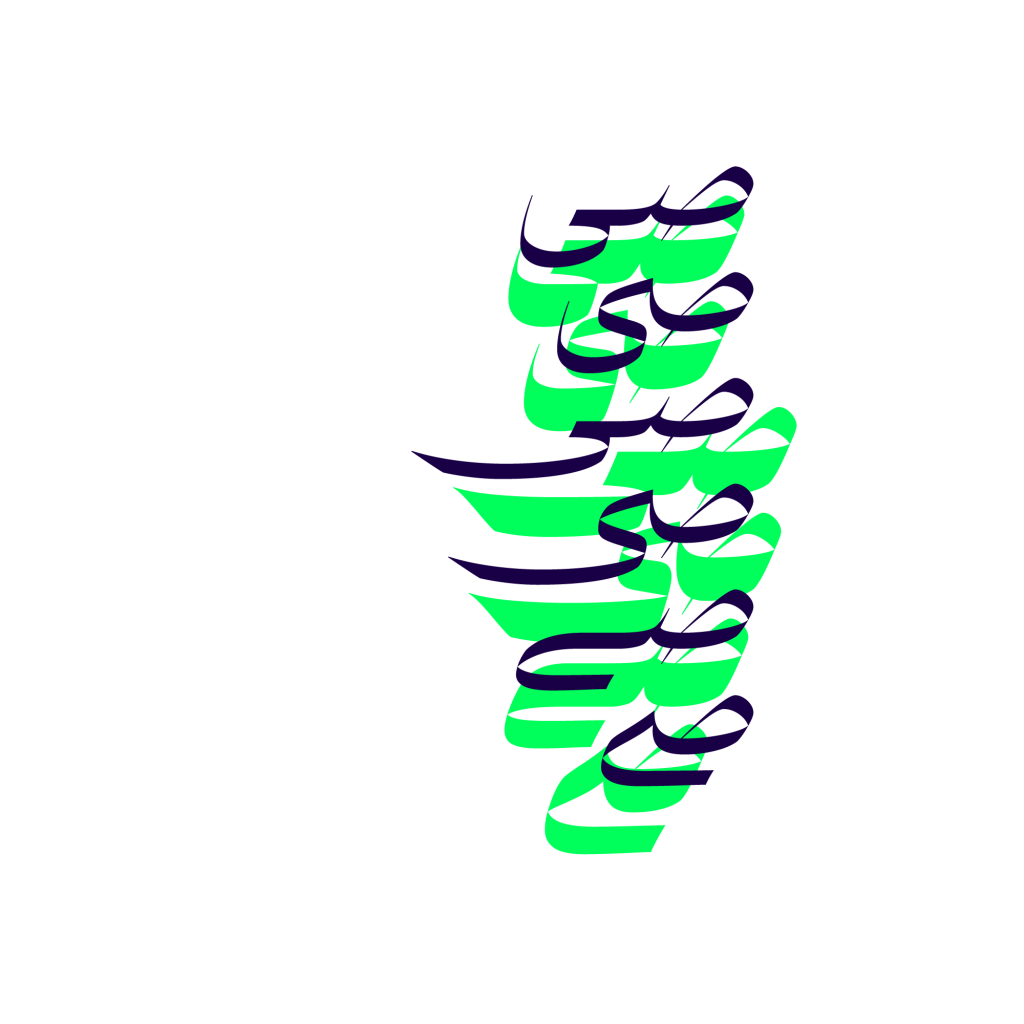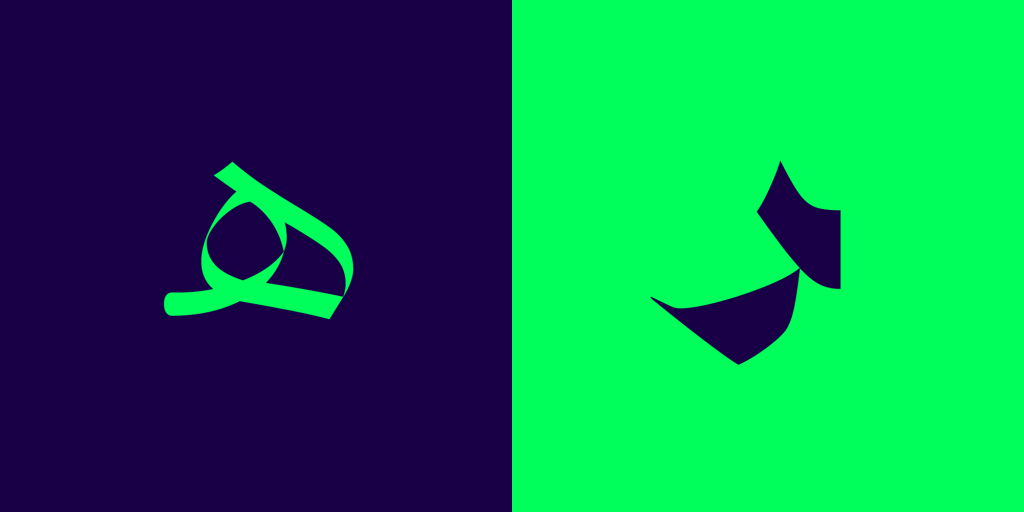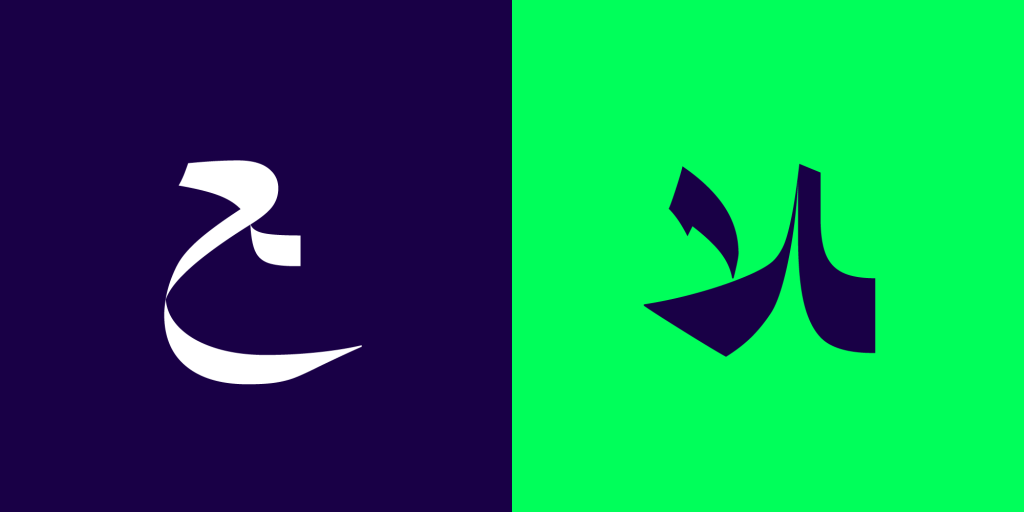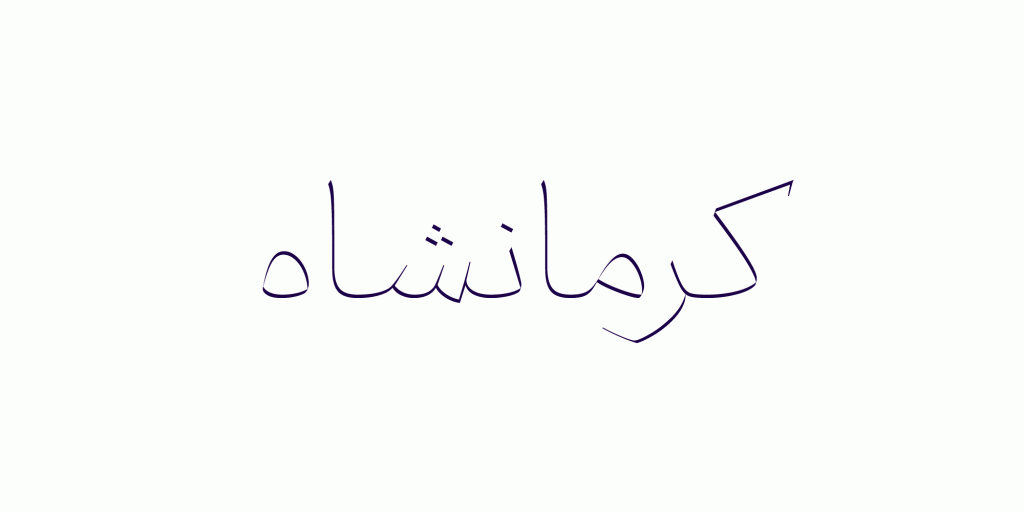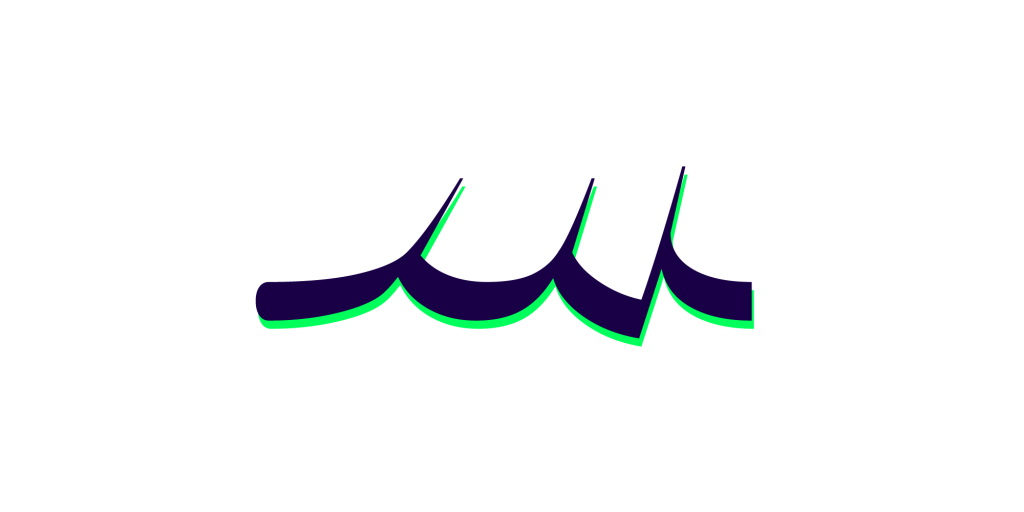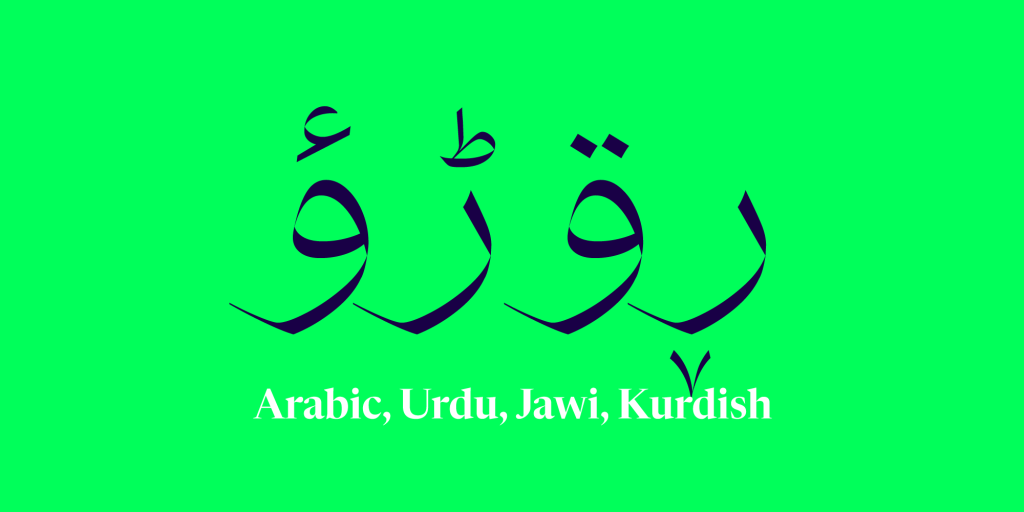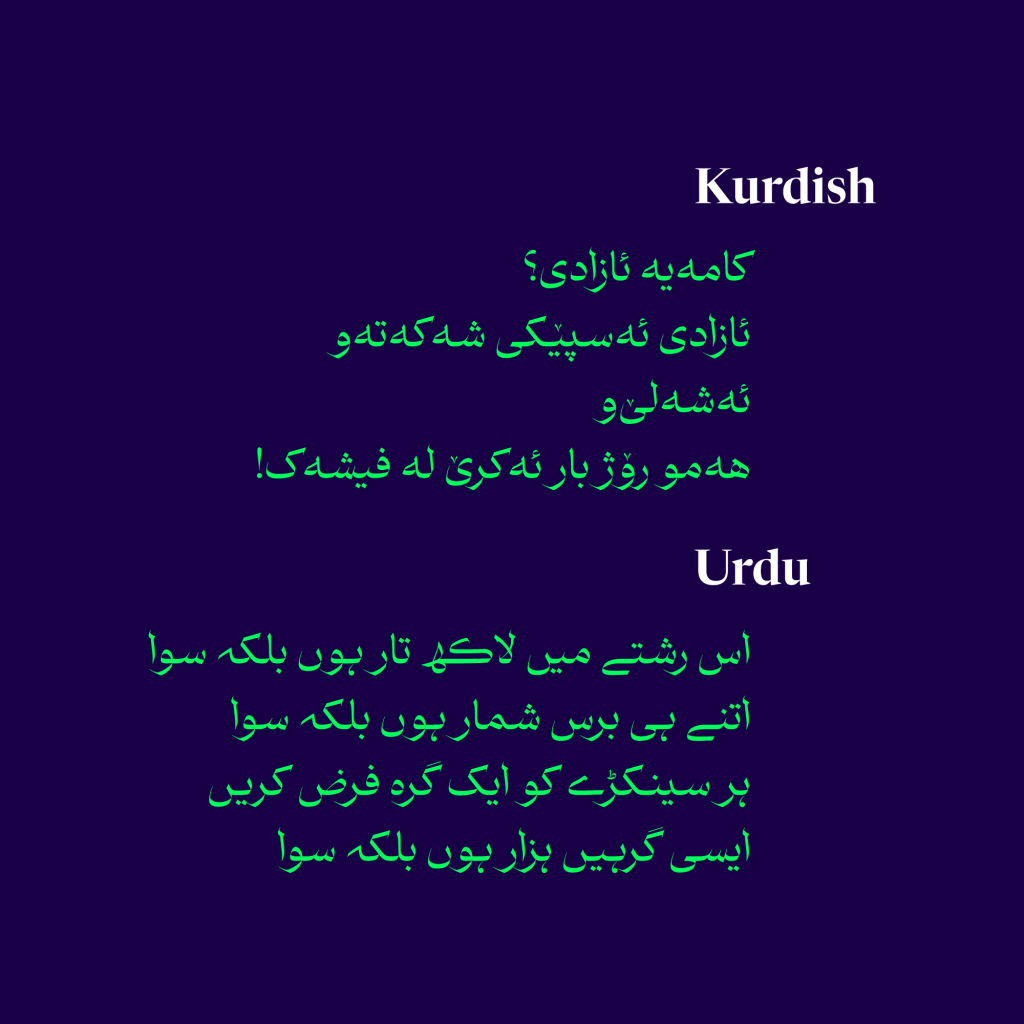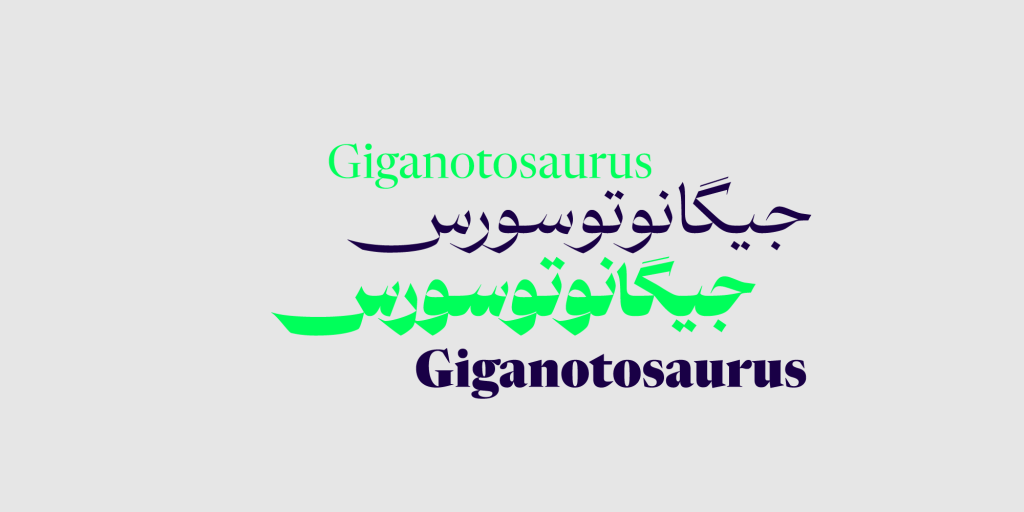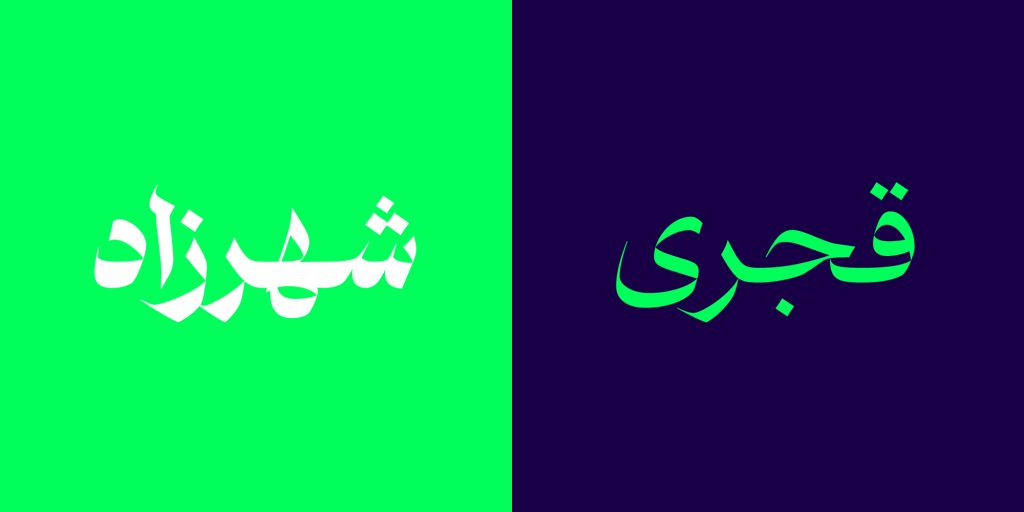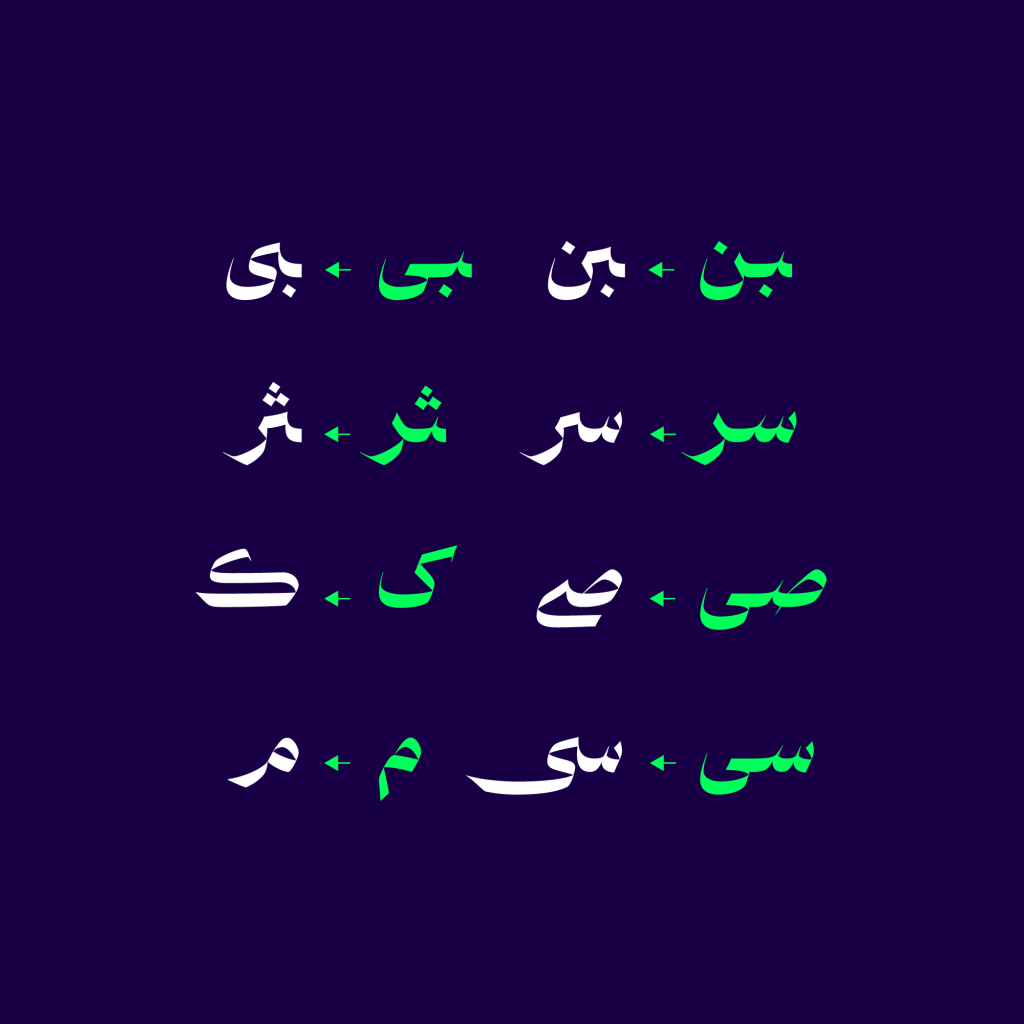
فونت پیکان قلمی که همانند نام پیکان تند و تیز و برنده است شجاع جسور و جدی است. این قلم از خانواده نسخ مناسب برای تیتر ها و متون کوتاه است تا نگاه مخاطب را در کسری از ثانیه جذب کند.
فونت پیکان قلمی با کنتراست ضخامتی بالا
قائده مند این خانواده توسط آقای رضا بختیاری طراح نام آشنای تایپوگرافی ایجاد شده است.همانند نام خود که پیکان به معنی تیز و برنده فرم های حروف و ساختارش شکل گیری شده است. با اندکی دقت می توان فهمید که دارای کنتراستی اغراق آمیز و زیاد در سطح و ضخامت است.
تمرکز در این تایپ فیس بر استفاده از برجسته ‌سازی شکستگی‌ها و زوایای تند و تیز نسبت به  سطوح هموار و صاف است. این نوع تمرکز و شباهت در طراحی فرم های حروف در فونت قرنطینه هم به مانند این قلم در نظر گرفته شده است.
رفتار های پویا و تغییر ضخامت سطحی هیجان و جاذبه ای خاص به این نوع از تایپ فیس های فارسی داده است. اسکلتی پر از خط‌های صاف دارد و تنه‌اش پر از فرم‌های تیز و بُرنده است . به همین خاطر جدی است و جسور و دارای ویژگی نمایشی است تا در کمترین زمان ممکن نگاه مخاطب را به خود جلب کند.
این تایپ فیس مناسب متون کوتاه و عناوین و تیتر های مطبوعاتی و تبلیغاتی از صنعت تیتر و چاپ گرفته تا دنیای وب و دیجیتال است. همچنین می توان از این قلم در طراحی های مرتبط با فشن و برای برندهای لوکس نیز استفاده کرد
ایده اصلی در شکل گیری پیکان تایپ فیس شفیق بوده که طراح را مشتاق تر کرده تا فونتی با این اتمسفر اما با اغراق‌هایی بسیار بیش‌تر طراحی کند.
پشتیبانی از وریبل فونت و تنوع اوزان
یکی از مزیت های سال های اخیر هر تایپ فیس و قلم پشتیبانی از فایل متغییر یا Variable Font است. دارا بودن تمامی وزن های طراحی شده در یک فایل مزیتی فوق العاده را ایجاد کرده که سبب کاهش حجم و بارگزاری سریع  صفحات  وب می شود. پیکان همچنین دارای تنوع وزنی تقریبا کاملی برای طراحی های شما است.
این قلم با پشتیبانی از ۶وزن (Thin, Light, Regular, Bold, Black, ExtraBlack)  پاسخ دهنده به نیاز طراحان است. در زیر تصاویری نمونه از این تایپ فیس را برای شما دوستان عزیز قرار داده ایم
زبان‌های پشتیبانی شده :
فارسی , انگلیسی , اُردو , کوردی